타이포그래피 실수: 제목과 본문의 자간 조정이 필요한 상황과 구체적 수치
자간은 제목과 본문에서 각각 -0.02em0.05em 범위로 조정하는 것이 실용적인 출발점입니다. 큰 제목은 대체로 좁히고 작은 본문은 기본값을 유지하거나 조금 넓히되, 서체·굵기·화면 크기에 따라 실제 문장을 보며 판단해야 합니다. 숫자만 일괄 적용하는 것은 오히려 흔한 타이포그래피 실수가 됩니다.
TL;DR 핵심 요약
타이포그래피 실수를 줄이기 위해 제목과 본문의 자간을 -0.02em~0.05em 범위에서 조정하는 기준과 한글 서체별 점검 절차를 설명합니다.
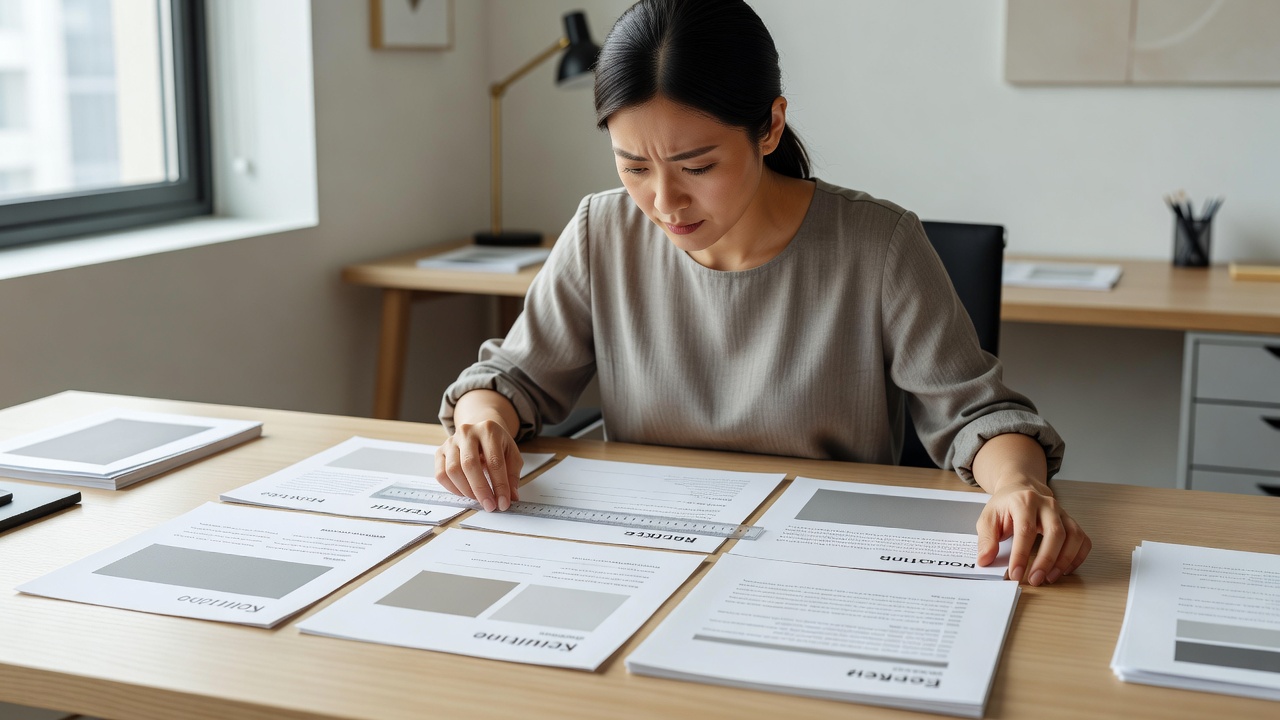
자간 조정이 필요한 이유
자간은 연속된 글자 사이의 간격이며, 문장 전체에 적용하는 조정을 트래킹이라고 부릅니다. 특정 글자 쌍만 다듬는 커닝과는 적용 범위가 다릅니다. 예를 들어 제목 전체가 성기다면 트래킹을 조절하고, ‘VA’나 숫자와 괄호 사이만 어색하다면 커닝을 확인해야 합니다.
Adobe의 커닝·트래킹 안내에 따르면, 글꼴에는 특정 문자 조합을 위한 간격 정보가 포함될 수 있습니다. 따라서 먼저 커닝을 metrics 또는 auto로 활성화하고, 그래도 시각적 밀도가 맞지 않을 때 전체 자간을 조정하는 순서가 합리적입니다.
자간이 지나치게 좁으면 글자 덩어리가 뭉쳐 받침과 다음 초성이 붙어 보입니다. 반대로 너무 넓으면 단어보다 개별 글자가 먼저 보여 읽는 흐름이 끊깁니다. 자간은 장식 효과가 아니라 글자의 밀도와 단어 인식을 정돈하는 미세 조정입니다.
제목과 본문의 권장 범위
다음 수치는 완성값이 아니라 1차 테스트 범위입니다. 1em은 현재 글자 크기를 기준으로 하므로, -0.02em은 글자 크기의 **2%**만큼 간격을 줄인다는 뜻입니다. 예를 들어 40px 제목에서 -0.02em은 약 -0.8px, 16px 본문에서 0.02em은 약 0.32px에 해당합니다.
| 적용 대상 | 시작값 | 시험 범위 | 판단 기준 |
|---|---|---|---|
| 32px 이상 큰 제목 | -0.02em | -0.02em–0.02em | 글자 사이의 흰 공간이 균일한가 |
| 20–31px 소제목 | -0.01em | -0.02em–0.03em | 굵은 획이 서로 붙지 않는가 |
| 15–19px 본문 | 0 | -0.01em–0.03em | 여러 줄을 편하게 읽을 수 있는가 |
| 12–14px 캡션 | 0.02em | 0–0.05em | 작은 화면에서도 글자가 분리되는가 |
| 영문 대문자 레이블 | 0.04em | 0.02em–0.08em | 단어 형태가 흐트러지지 않는가 |
본문에 무조건 -0.02em을 적용해 화면에 더 많은 글자를 넣는 방식은 피해야 합니다. 특히 14px 이하의 작은 글자에서는 좁은 자간이 해상도와 안티앨리어싱의 영향을 크게 받습니다. 기본값에서 0.01em씩 움직이며 실제 기기에서 비교하는 편이 안전합니다.
자간을 반드시 확인해야 하는 상황
서체, 굵기, 크기를 바꾸면 같은 자간 값도 전혀 다르게 보입니다. 굵은 제목, 숫자가 많은 가격표, 한글과 영문이 섞인 메뉴, 대문자 버튼, 중앙 정렬된 짧은 문구는 간격 차이가 쉽게 드러나므로 별도 점검이 필요합니다.
| 상황 | 자주 보이는 문제 | 우선 조치 |
|---|---|---|
| 굵은 한글 제목 | 네모꼴이 뭉쳐 보임 | -0.01em부터 축소 시험 |
| 가는 본문 서체 | 글줄이 흩어져 보임 | 기본값 또는 -0.01em 시험 |
| 영문 대문자 버튼 | 글자가 답답하게 붙음 | 0.02em–0.05em 확대 |
| 숫자·단위 조합 | 10,000원 간격이 불균일함 | 숫자 기능과 개별 커닝 확인 |
| 반응형 모바일 | 줄바꿈 위치가 갑자기 변함 | 360px 전후 화면에서 재검사 |
| 웹폰트 로딩 전후 | 대체 글꼴과 폭이 달라짐 | 두 상태의 넘침 여부 확인 |
한 줄 제목의 마지막 글자만 다음 줄로 넘어갈 때 자간으로 억지로 맞추는 것도 타이포그래피 실수입니다. 먼저 문구 길이, 컨테이너 폭, 글자 크기를 검토하고 자간은 마지막 미세 조정에 사용해야 합니다.
한글 자간은 어떻게 조정해야 할까?
한글은 초성·중성·종성이 한 글자 안에서 네모꼴을 이루므로 영문보다 글자 외곽의 흰 공간이 규칙적으로 느껴집니다. 그러나 ‘기’, ‘니’처럼 오른쪽이 열린 글자와 ‘롤’, ‘폼’처럼 획이 찬 글자가 이어지면 같은 수치에서도 간격이 달라 보일 수 있습니다. 따라서 자간 값보다 문장 전체의 흰 공간 리듬을 먼저 봐야 합니다.
본문은 최소 3줄 이상, 가능하면 실제 서비스 문장으로 시험합니다. 제목도 단어 하나만 보지 말고 조사, 숫자, 괄호가 포함된 후보를 함께 비교합니다. 가나다라마바사처럼 균일한 시험 문자열만 사용하면 실제 조판에서 생기는 문제를 놓치기 쉽습니다.
W3C CSS Text 사양에 따르면, letter-spacing은 normal 또는 길이 값으로 글자 사이의 추가 간격을 지정합니다. 웹에서는 px보다 글자 크기에 비례하는 em이 반응형 조정에 편리하지만, 양쪽 정렬에서는 브라우저가 간격을 추가로 조절할 수 있으므로 왼쪽 정렬 결과와 동일하다고 가정하면 안 됩니다.
단계별 자간 조정 절차
먼저 사용할 서체 파일과 굵기를 확정하고 커닝 기능을 켭니다. 다음으로 제목은 -0.02em, 본문은 0, 작은 캡션은 0.02em에서 시작합니다. 한 번에 큰 폭으로 바꾸지 말고 0.01em 단위로 전후 값을 만들어 비교하면 변화의 원인을 구분하기 쉽습니다.
- 실제 제목과 본문을 각각 3개 이상 준비합니다.
- 자간 외의 글자 크기·행간·너비를 고정합니다.
- 기준값과 ±0.01em 시안을 나란히 비교합니다.
- 데스크톱과 360px 모바일 화면에서 줄바꿈을 확인합니다.
- 굵기 400과 700, 숫자·영문 혼용 문장을 함께 검사합니다.
- 선택한 값을 디자인 토큰이나 CSS 변수로 기록합니다.
검수할 때는 화면을 확대해 글자 한 쌍만 보는 것보다 100% 배율에서 문단을 읽는 과정이 중요합니다. 약 2–3m 거리에서 큰 제목의 전체 밀도를 보고, 본문은 평소 읽는 거리에서 속도와 피로도를 살핍니다. 인쇄물이라면 실제 크기로 1회 이상 출력해 모니터 결과와 비교합니다.
흔한 타이포그래피 실수와 해결법
가장 흔한 문제는 모든 요소에 같은 음수 자간을 적용하는 것입니다. 제목을 단단하게 만든 값이 본문에서는 가독성을 떨어뜨릴 수 있습니다. 제목·본문·캡션·버튼별 토큰을 나누고, 상속된 letter-spacing이 작은 텍스트까지 내려가지 않는지 확인해야 합니다.
또 다른 타이포그래피 실수는 자간으로 행간과 글줄 길이 문제까지 해결하려는 것입니다. 본문이 답답하면 먼저 1.5~1.7 정도의 행간과 한 줄 약 40–70자의 길이를 점검해야 합니다. 단어 사이가 문제라면 자간이 아니라 어간이나 정렬 방식을 살펴야 합니다.
마지막으로 특정 시안에서만 보기 좋은 값을 고정하지 마세요. 핵심은 제목 -0.02em, 본문 0 같은 기준점에서 출발해 서체와 매체에 맞춰 0.01em씩 검증하는 것입니다. 프로젝트의 한글·영문·숫자 조합이 복잡하다면 실제 화면을 준비해 타이포그래피 검수나 디자인 상담을 요청하는 것도 효율적인 방법입니다.
제목 자간은 항상 좁혀야 하나요?
아닙니다. 굵고 큰 제목은 -0.02em부터 시험할 수 있지만, 장체나 획이 복잡한 서체는 기본값이 더 안정적일 수 있습니다. 글자의 흰 공간이 이미 좁다면 양수 값도 비교해야 합니다.
본문에 적합한 자간은 얼마인가요?
16px 안팎의 한글 본문은 0에서 시작하고, 필요할 때 -0.01em~0.03em 범위에서 조정하세요. 최소 3줄을 실제로 읽어 본 뒤 결정하는 것이 좋습니다.
자간과 커닝은 무엇이 다른가요?
자간 조정인 트래킹은 선택한 문장 전체의 간격을 일정하게 바꿉니다. 커닝은 특정 글자 두 개 사이의 시각적 간격을 다듬는 작업입니다.
CSS에서는 어떤 단위를 사용해야 하나요?
반응형 웹에서는 글자 크기에 비례하는 em이 관리하기 편합니다. 다만 정확한 시각 보정이 필요한 고정형 그래픽에서는 px나 디자인 도구의 트래킹 단위를 사용할 수 있습니다.
자간을 바꾸면 접근성에 문제가 생기나요?
너무 좁은 값은 작은 글자의 식별과 읽기 흐름을 방해할 수 있습니다. 확대 화면, 모바일, 긴 문단에서 겹침이나 잘림이 없는지 확인하고 사용자가 지정한 텍스트 간격을 CSS가 강제로 무효화하지 않도록 점검해야 합니다.